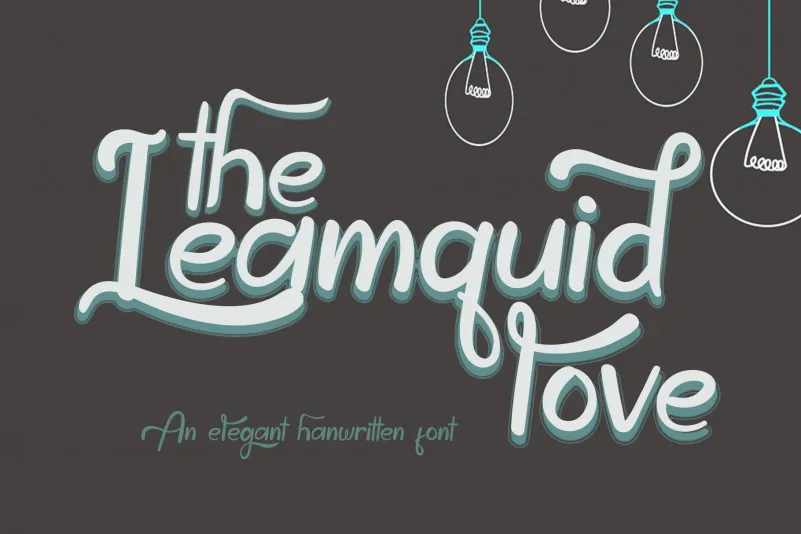
The Leamquid Love Script Font – Download Grátis
A fonte ‘The Leamquid Love Script Font’ é perfeitamente adequada para aqueles que buscam uma mistura sofisticada com uma pitada contemporânea e fresca. Embora mantenha suas influências clássicas da calligrafia, evolui de maneira a se adaptar ao mundo moderno. Esta fonte oferece grande versatilidade, ideal para um leque amplo de ideias criativas. Seja ela usada em assinaturas ou títulos de documentos, ou mesmo no design de estaçãoaria e convites personalizados, o ‘Leamquid Love Script’ torna-se uma escolha perfeita para qualquer projeto que busque harmonia entre elegância e modernidade. Ideal tanto para designers profissionais quanto para criativos iniciantes, esta fonte é um investimento valioso na sua coleção de recursos gráficos.